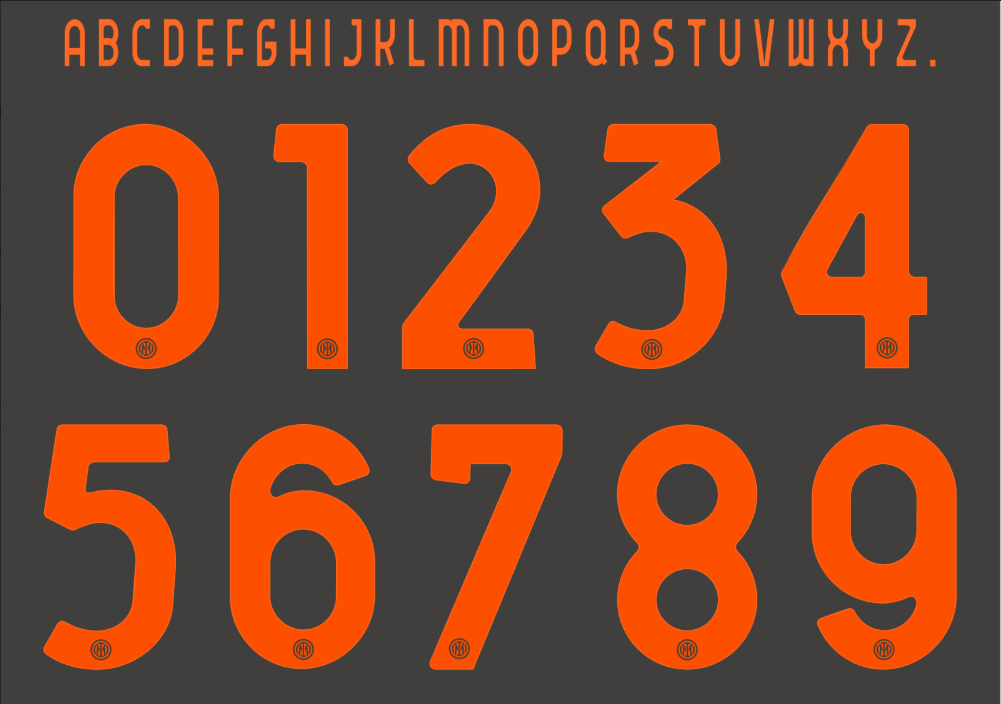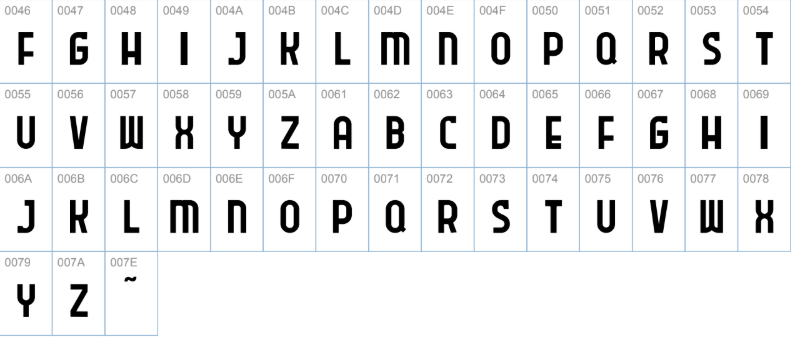
Quando se trata de unir moda e futebol, a Inter de Milão e a Nike formam uma das parcerias mais icônicas do mundo esportivo. A temporada 2025/26 não é exceção, e o lançamento do Fourth Kit (quarto uniforme) reforça a posição do clube Nerazzurri como uma marca global de lifestyle.
Geralmente destinados a jogos especiais da Serie A ou competições europeias, os quartos uniformes da Inter costumam romper barreiras criativas, trazendo designs arrojados e futuristas. A tipografia utilizada nestas peças é fundamental para compor o visual: ela precisa ser legível, moderna e estar em sintonia com a estética ousada proposta pela marca norte-americana.
Neste artigo, disponibilizamos para download a fonte Inter Fourth 2025 – 26, uma recriação digital detalhada, inspirada na tipografia estampada nas camisas dos craques que defendem as cores de Milão.
Detalhes técnicos da fonte
Estilo visual da tipografia
A tipografia do quarto uniforme da Inter de Milão para a temporada 2025/26 reflete a identidade inovadora da Nike. Ao contrário das fontes clássicas, este estilo busca inspiração no streetwear e na arquitetura moderna de Milão.
- Design: A fonte apresenta caracteres sólidos e imponentes. Geralmente, as fontes dos Fourth Kits da Inter fogem do padrão da liga italiana, permitindo numerações com cortes geométricos mais agressivos ou contornos estilizados que geram efeito de movimento.
- Aplicação: Nos uniformes oficiais, esta fonte é aplicada de forma a contrastar fortemente com o padrão da camisa (que muitas vezes possui texturas complexas ou misturas de cores). A legibilidade é priorizada, garantindo que nomes e números sejam visíveis tanto no estádio quanto nas transmissões digitais.
- Vibe: Transmite tecnologia, velocidade e elegância urbana, características centrais da marca “IM” (Inter Milano).